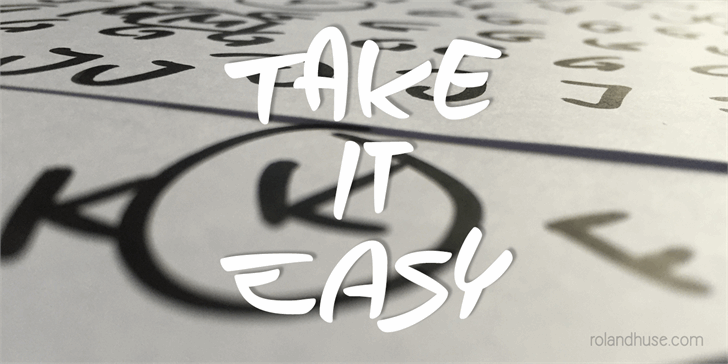
A fonte Take It Easy é uma escolha perfeita para quem busca um estilo artesanal e descompromissado. Desenhada pelo designer Hamilton, ela transmite uma sensação descontraída e quixotesca com sua forma desequilibrada de letra maiúscula escrita a mão. Essa fonte é ideal para aqueles que procuram um touch único e inovador para seus projetos digitais, seja em layouts de newsletters, identidades visuais ou até mesmo como gráficos publicitários criativos. O Take It Easy oferece uma versão elegante e fluida dos caracteres, tornando-a versátil o suficiente para incorporar em um amplo range de aplicativos. Quebre a monotonia da sua próxima produção visual com esta fonte que desenhou-se como se fosse escrita a mão, sem comprometer nenhuma característica essencial da ideia original.